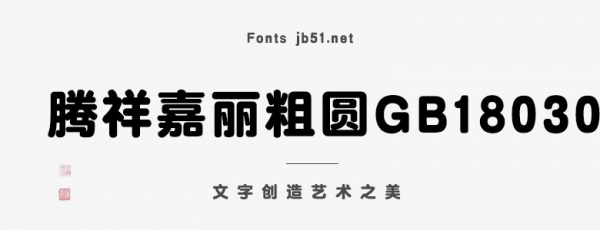
騰祥嘉麗粗圓GB18030字體是一款不錯的藝術(shù)字體,由騰祥字庫出品,這款字體筆畫光潔柔美、粗細均勻、間架結(jié)構(gòu)端正、重心平穩(wěn)適合應(yīng)用于藝術(shù)設(shè)計、平面宣傳設(shè)計、網(wǎng)頁設(shè)計,書法字帖等領(lǐng)域,需要的朋友可以前來本站下載。
騰祥嘉麗圓體系列字庫是騰祥公司自主精心設(shè)計的圓體家族系列字庫。共有8個粗細,各個粗細之間風(fēng)格一致,每款字庫數(shù)萬個字符風(fēng)格一致。字體風(fēng)格:其字懷大但結(jié)構(gòu)并不松散,字面比傳統(tǒng)黑體飽滿但比舊式圓體小,字形稍扁方但視覺上看似正方。每個字的轉(zhuǎn)角、圓頭、勾形都有極好的光潔度。筆型嚴(yán)謹(jǐn)、規(guī)范。每個字都經(jīng)過精心設(shè)計,筆畫光潔柔美、粗細均勻、間架結(jié)構(gòu)端正、重心平穩(wěn)。 此款字庫為騰祥嘉麗圓體系列的粗體一款,介于大圓與準(zhǔn)粗圓之間,共有27533個漢字,風(fēng)格統(tǒng)一。